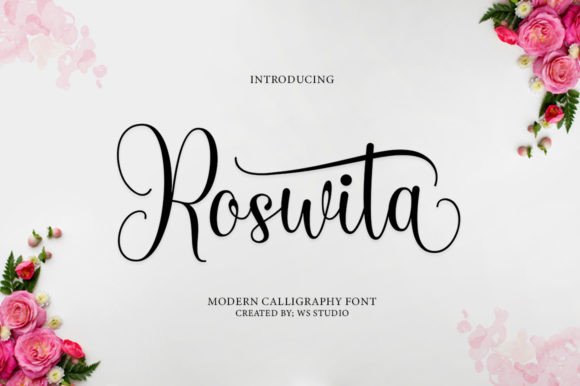
Roswita
Roswitaのような高品質の素材をお探しの場合、このプレミアムパッケージはクリエイティブなプロジェクトに素晴らしい選択です。
精密に作られたRoswitaは、クリーンなベクター、滑らかなタイポグラフィ、そして安心のための商用ライセンスを提供します。
POD(オンデマンド印刷)製品、結婚式の招待状、またはソーシャルメディアのグラフィックを作成している場合でも、Roswitaは理想的です。